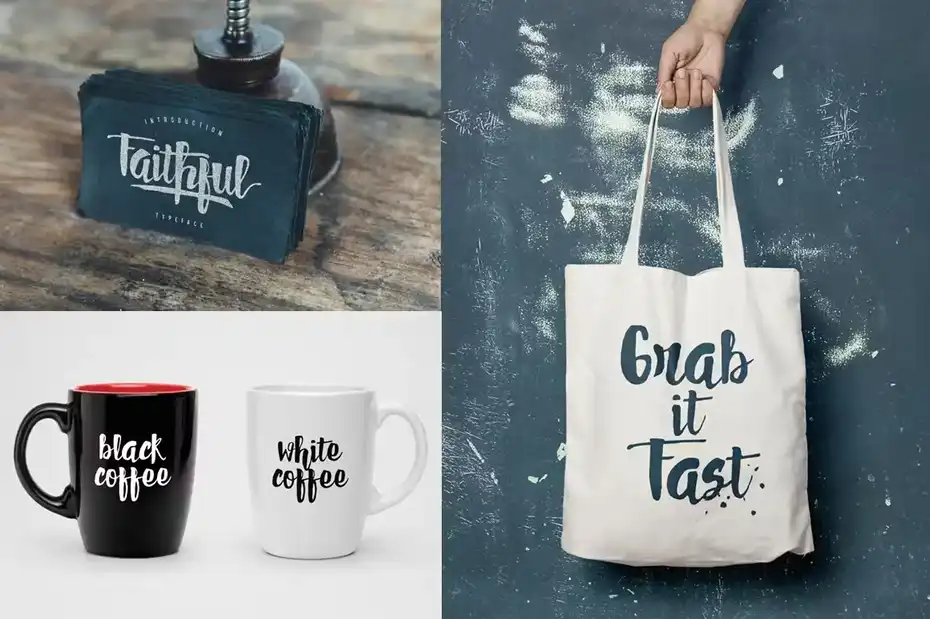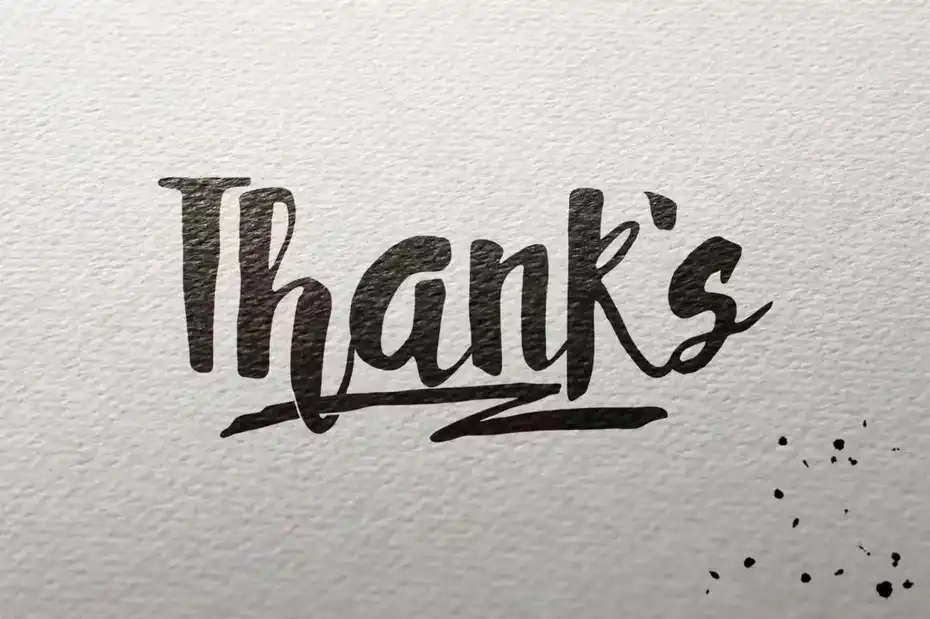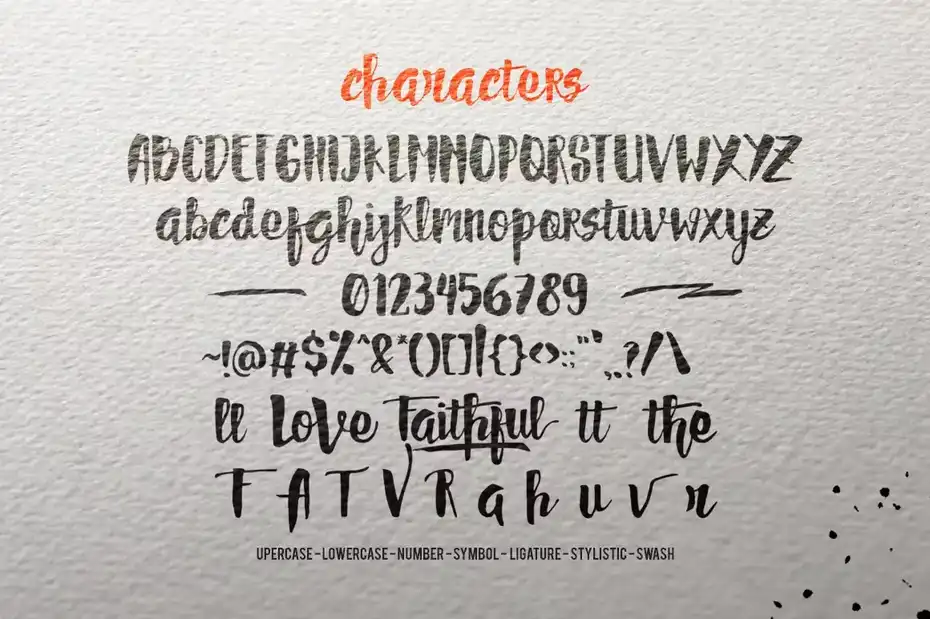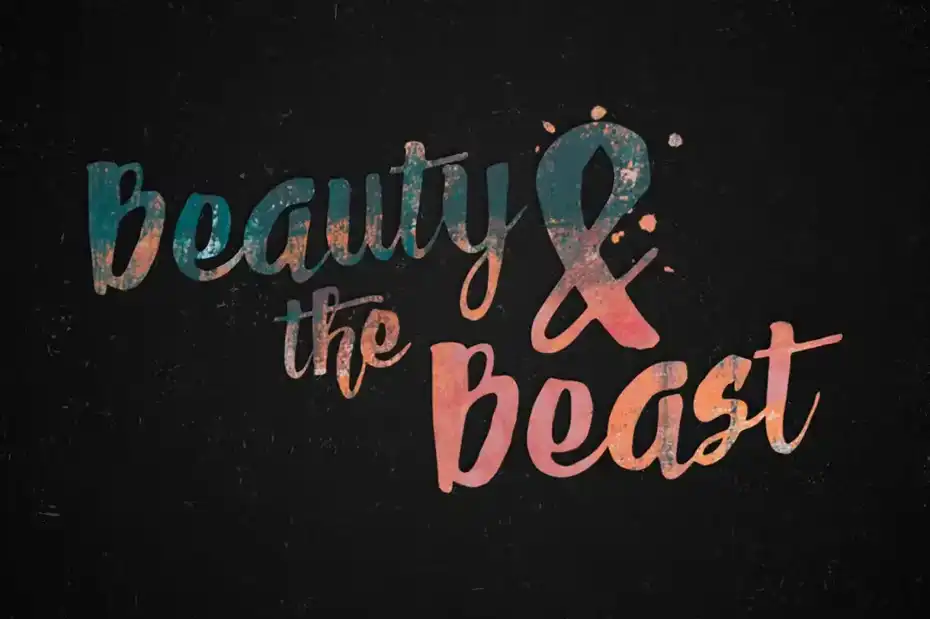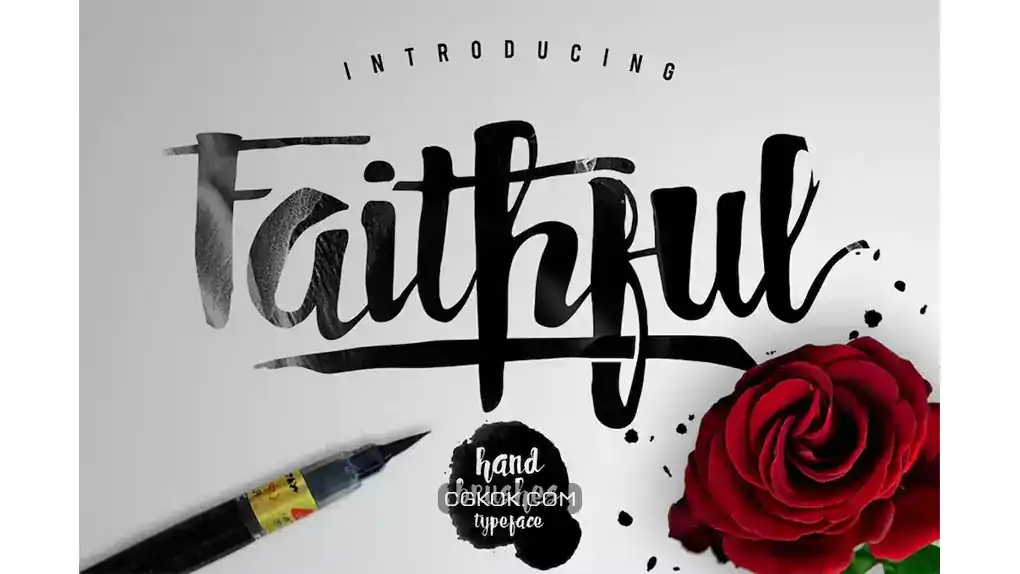
دانلود فونت انگلیسی دست نویس Faithful Typeface
فونت انگلیسی دست نویس Faithful Typeface : این مجموعه شامل یک فونت انگلیسی دست نویس است که برای لوگو، برندینگ، امضا، عنوان فیلم، کاور آلبوم، پوستر و غیره مناسب میباشد.